免费字体 在设计师的日常工作中尤为重要,当设计师在电脑前设计一幅完美的作品的同时,所使用的字体是非常关键的,选择一种既高质量又免费的字体,往往是非常耗时的。在制作软件中浏览电脑中无穷无尽的字体列表会让你眼花缭乱,下面搜集了 101 种免费字体,可以帮助您紧跟不断的潮流变化,并即时创建你的设计。
已经将字体分为几大类,了解如何使用serif、sans serif、script、modern、futuristic、wedding、holiday等字体,将这些字体融入您的作品中。
免费字体:Serif Fonts(衬线字体)
衬线字体的名字来源于从字母形式延伸出来的笔画,就像从字母“I”中伸出的腿一样。
衬线不只是为了纯粹的美学,它们实际上使文本对读者更易读。在排版的世界中,衬线字体被用于所有媒体、书籍、杂志、网站标题和社交图形等。
衬线的形状可以决定特定字体的色调。过渡衬线给人更传统和经典的感觉,而高对比度衬线看起来更现代和时尚。
就像所有字体都有独特的外观一样,衬线也有各种形状和大小。它们可以平滑地过渡到字体,使其外观更加圆润,或者它们可以突然连接到矩形板或三角形楔形的字母。
1. Abril Fatface
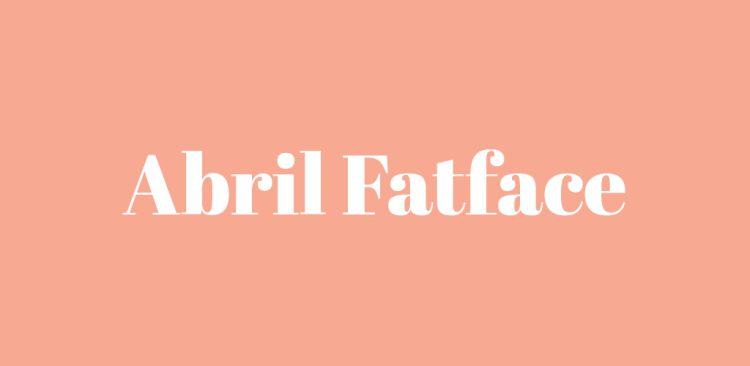
2. BioRhyme
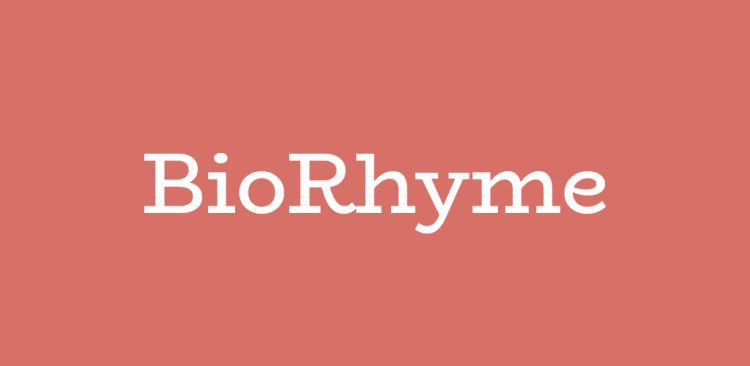
3.Blacker
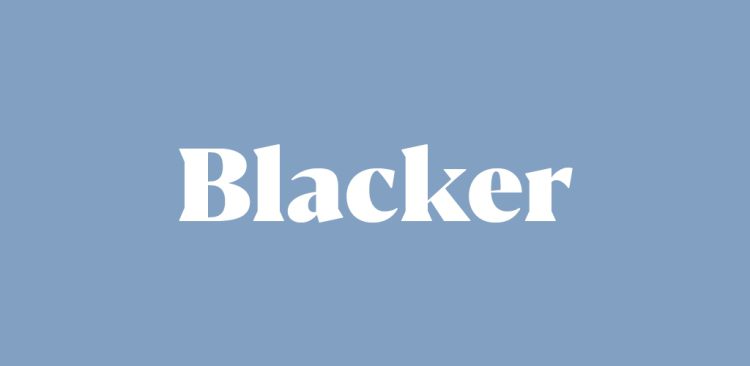
4.Charcuterie
5.Cooper Black
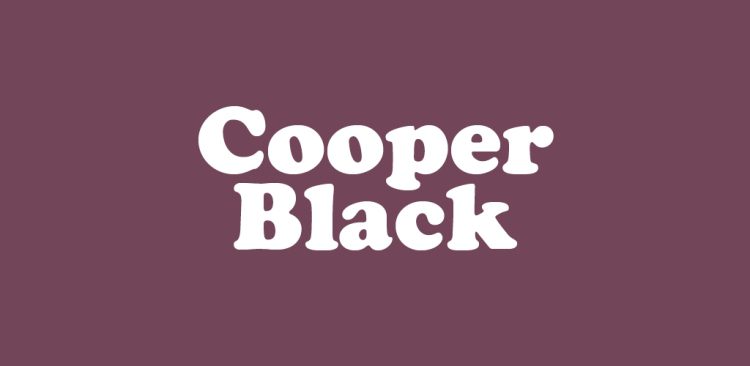
6.Gravitas One
7. Messenger
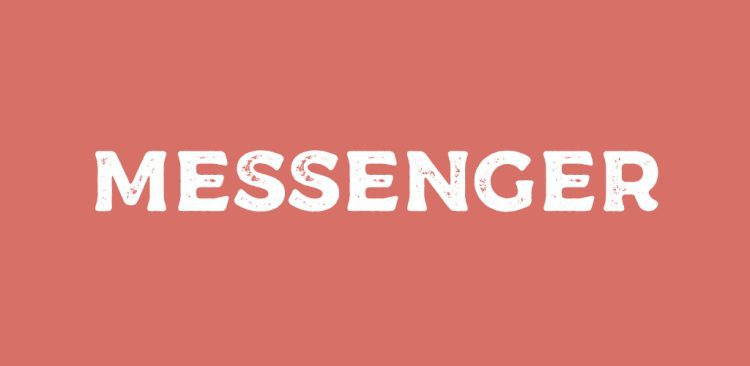
8.Portage
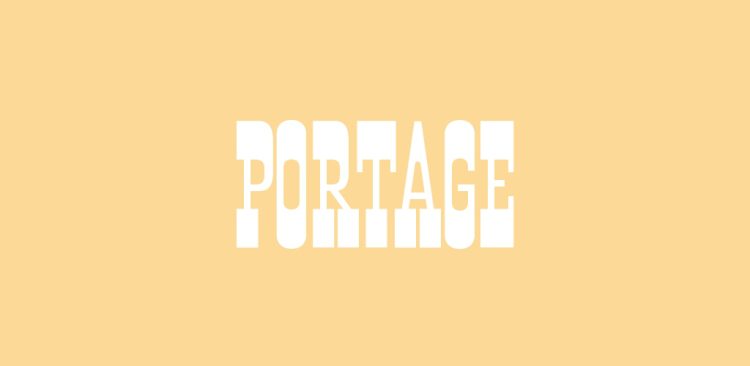
9. PT Serif
10. Questa Grande
11. Shrikhand
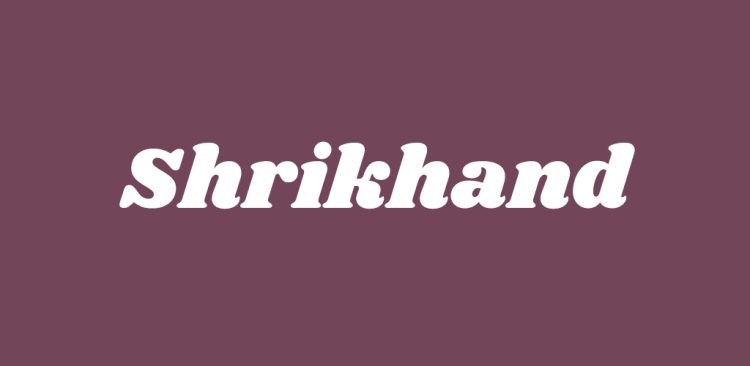
12. Stint Ultra Condensed
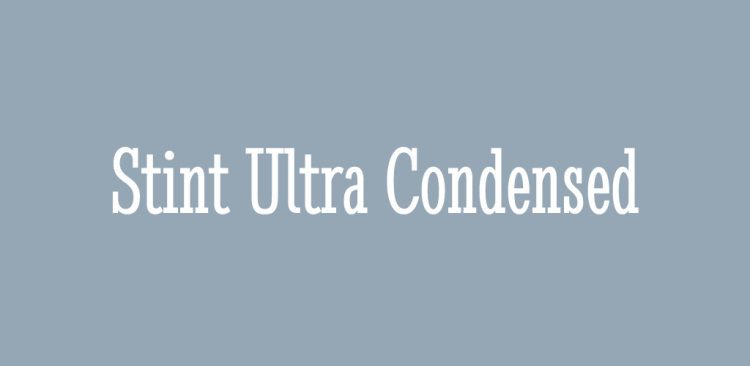
13. Stint Ultra Expanded
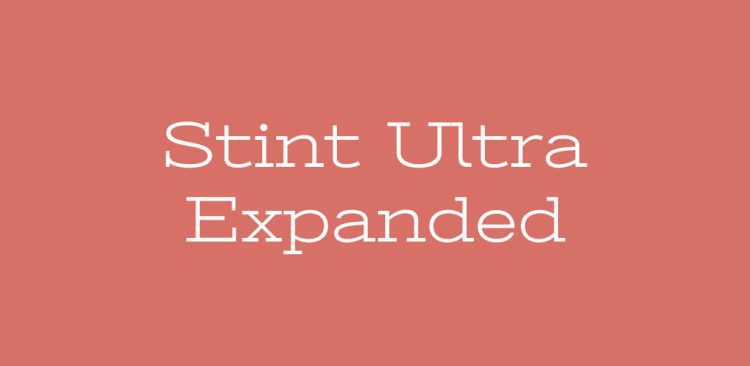
14. Tarif
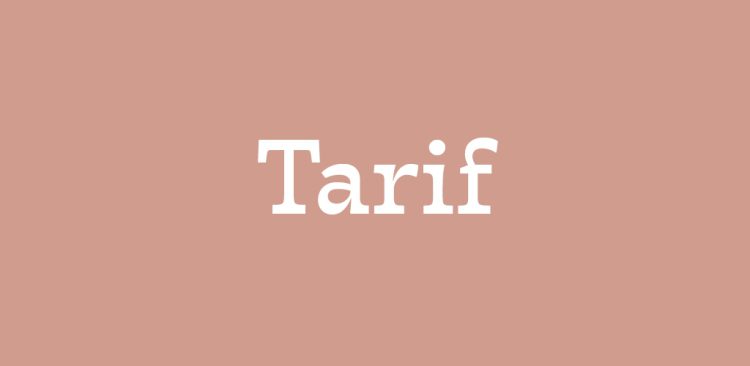
15. The Circus
16. Zilla Slab
免费字体:Sans Serif Fonts(无衬线字体)
衬线字体和无衬线字体之间的主要区别在于它在字母形式上没有笔画。顾名思义,无衬线的意思是“没有衬线”。
您会注意到每个字体都包含干净的单重线条,而不是过渡到衬线。无衬线字体可以是圆形的、几何的或书法的。
缺少衬线会极大地改变字体的色调。衬线字体营造出专业的色调,而无衬线字体则营造出更现代、更平易近人的色调。这就是为什么你经常看到初创企业、科技公司或休闲时尚品牌使用无衬线字体的原因。
17. Angelic Bonques
18. Averta
19. Bajern
20. Barlow
21. Bernier
22.Brandon Grotesque
23. Evogria
24. Gatwick
25. Guerrilla
26. Hackney
27.Ignite
28. Montserrat
29. Paytone One
30. Sansita
31.Watkins
32. Zing Rust
免费字体:Script Fonts(脚本字体)
脚本字体以其连接的字形和书法方法是优雅和精致的体现。
与 serif 或 sans-serif 字体不同,脚本通常用于标题或其他重要副本,因为较小的尺寸会失去可读性。
脚本的范围可以从带有圆形或有弹性的字体的非正式和俏皮到带有角度和戏剧性字体的正式和复杂的字体。
在为您的项目寻找字体样式时,请确保该样式与上下文一致。脚本字体通常保留用于豪华和女性化的应用程序。
您会发现它们被合并为婚礼请柬的字体、社交图形的 字体或名片的字体。
33. Blacksword
34. Buffalo
35. Eldwin script